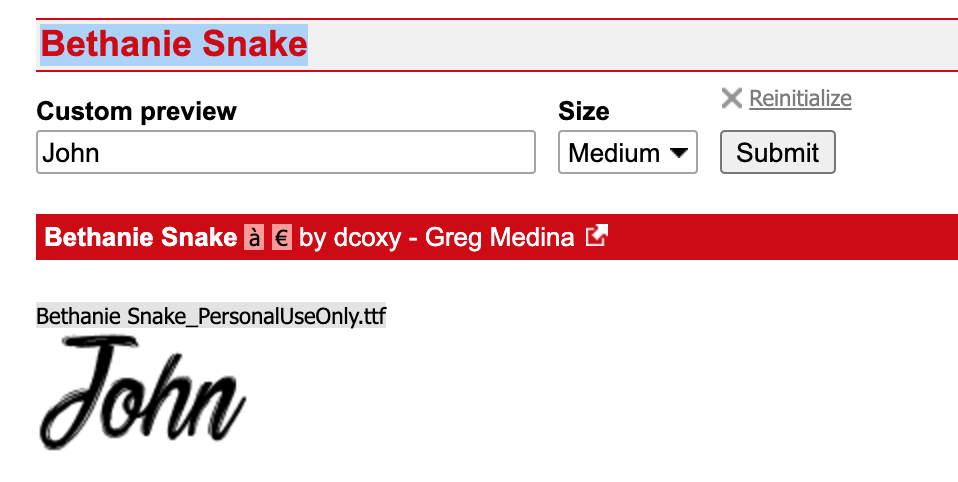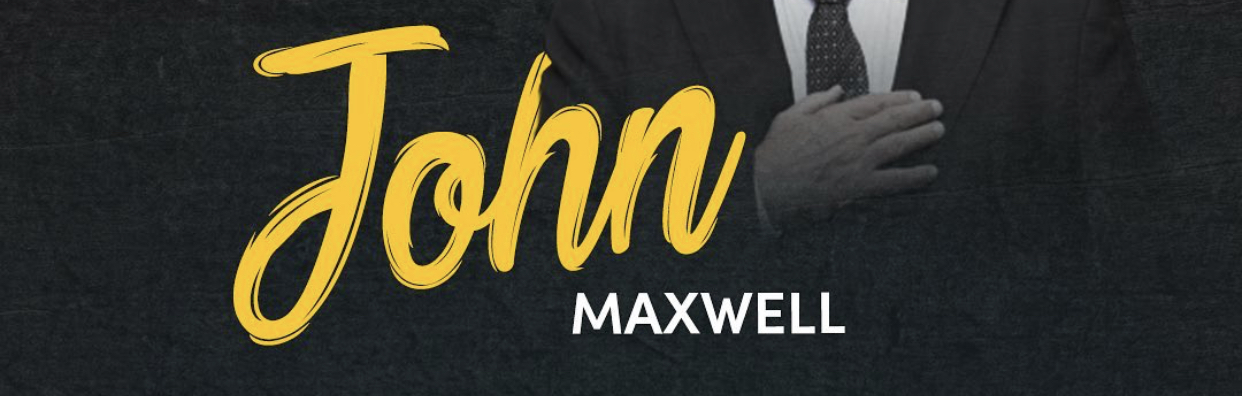
Bu font nedir? Bildiğiniz benzerleri var mı?
Bu el yazı fontu ne oluyor? Birde böyle başka bildiğiniz fontlar varsa önerir misiniz?
şu fontlara bakabilirsiniz: https://prnt.sc/uat2cu
teşekkür ederim ama daha el yazımı gibi duran arıyorum hocam fotoğraftaki gibi dışında çizgili şekilde gibi diyeyim
Bunun isminin 'Edo' olması lazım hocam
Hocam o halde sketch tarzı yazı tiplerine bakmanızı öneririm
fontun adı : Bethanie Snake => İnidr
Hocam buradan görseli tarayın. Benzer fontlar çıkar.